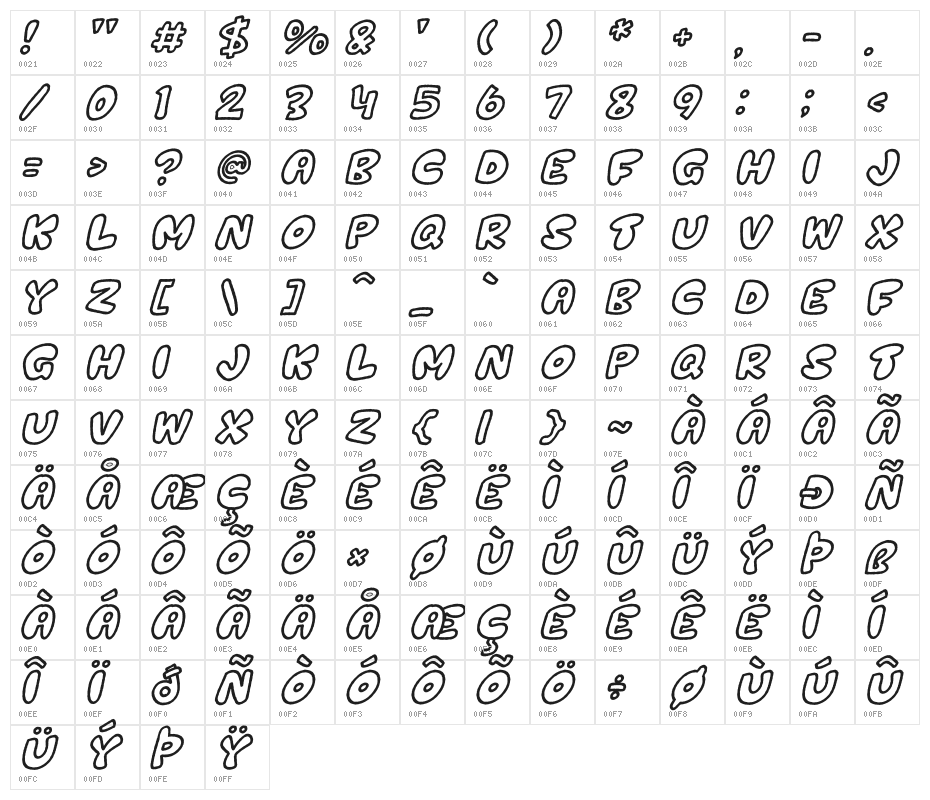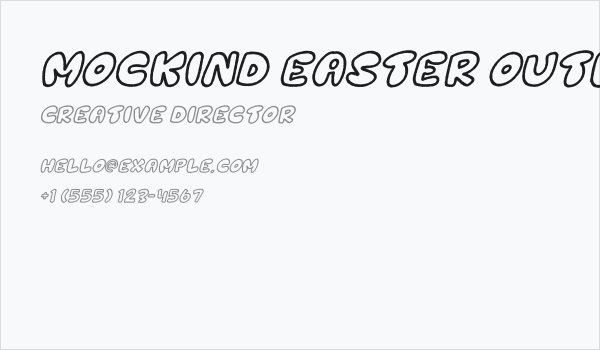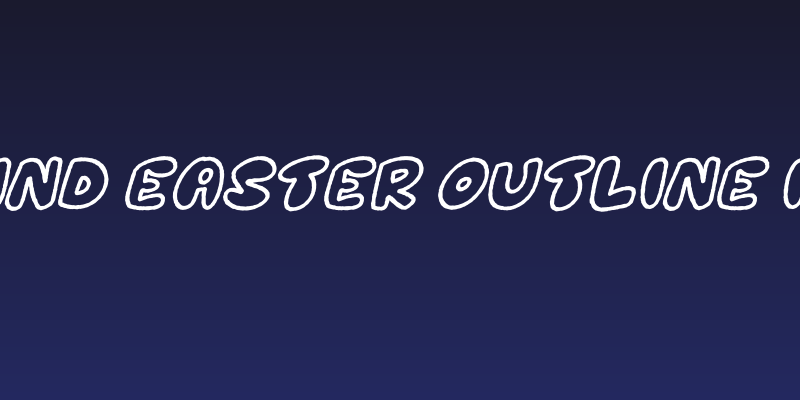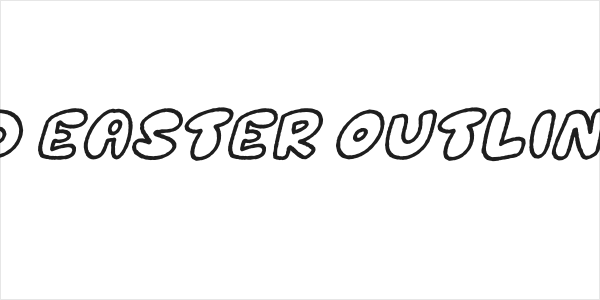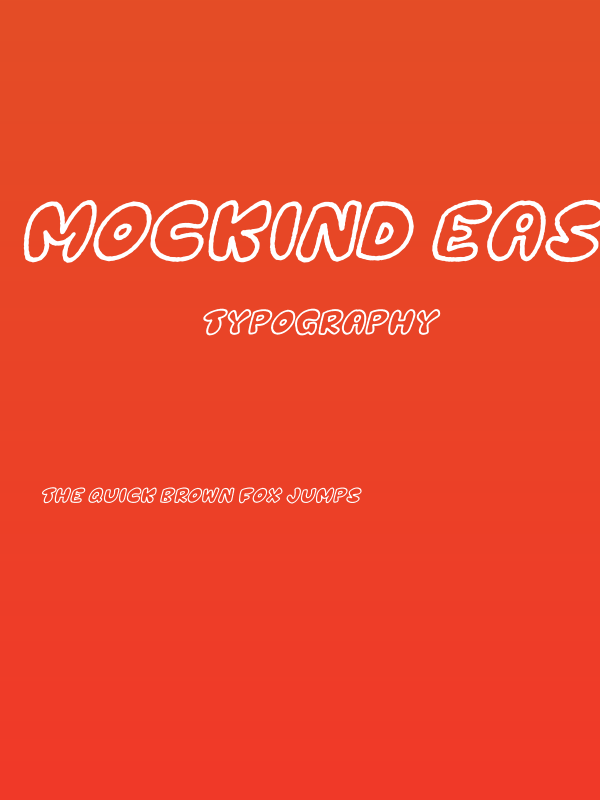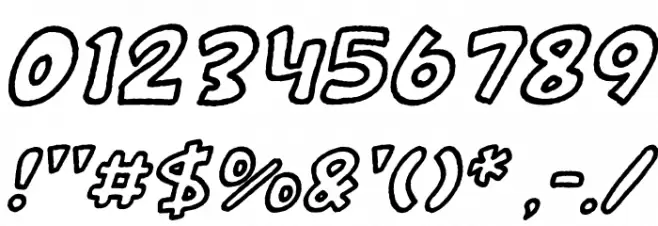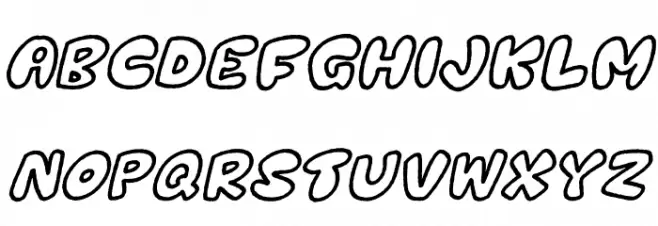
Mockind Easter Outline Italic Font
| Gesamtstil | Playful |
| Vorgeschlagene Projekte | Ideal for children's books, playful branding, party invitations, and casual posters. |